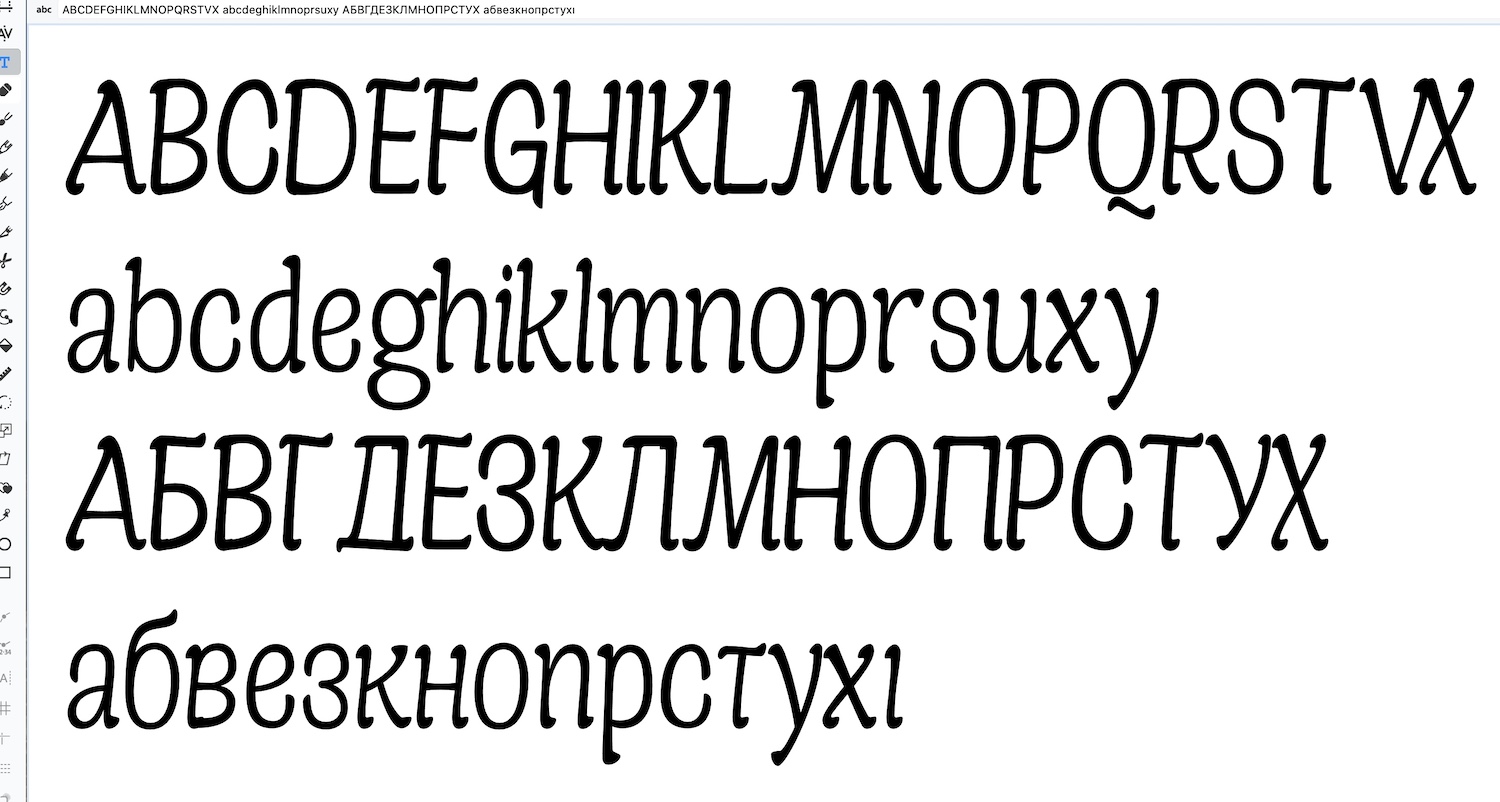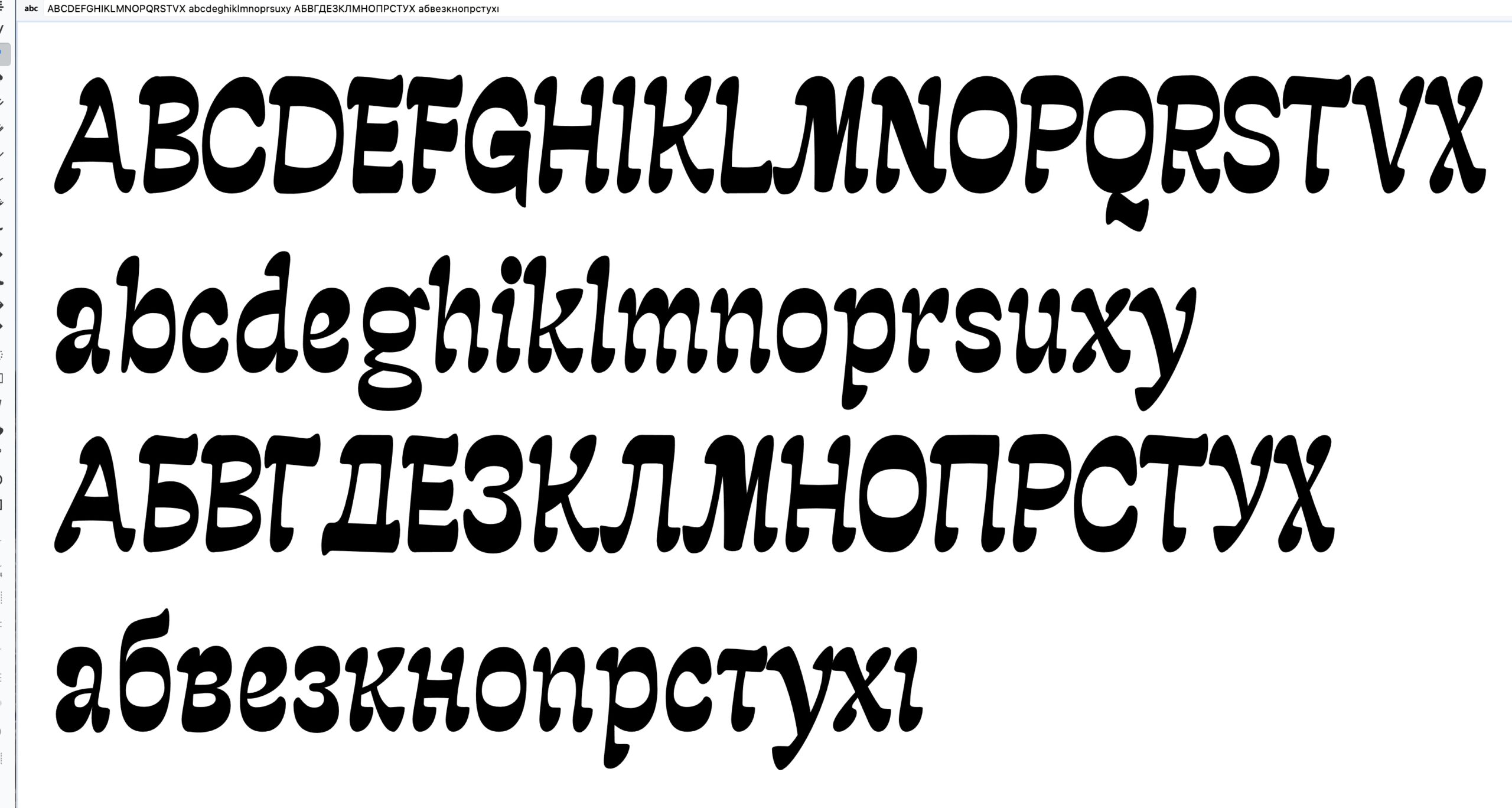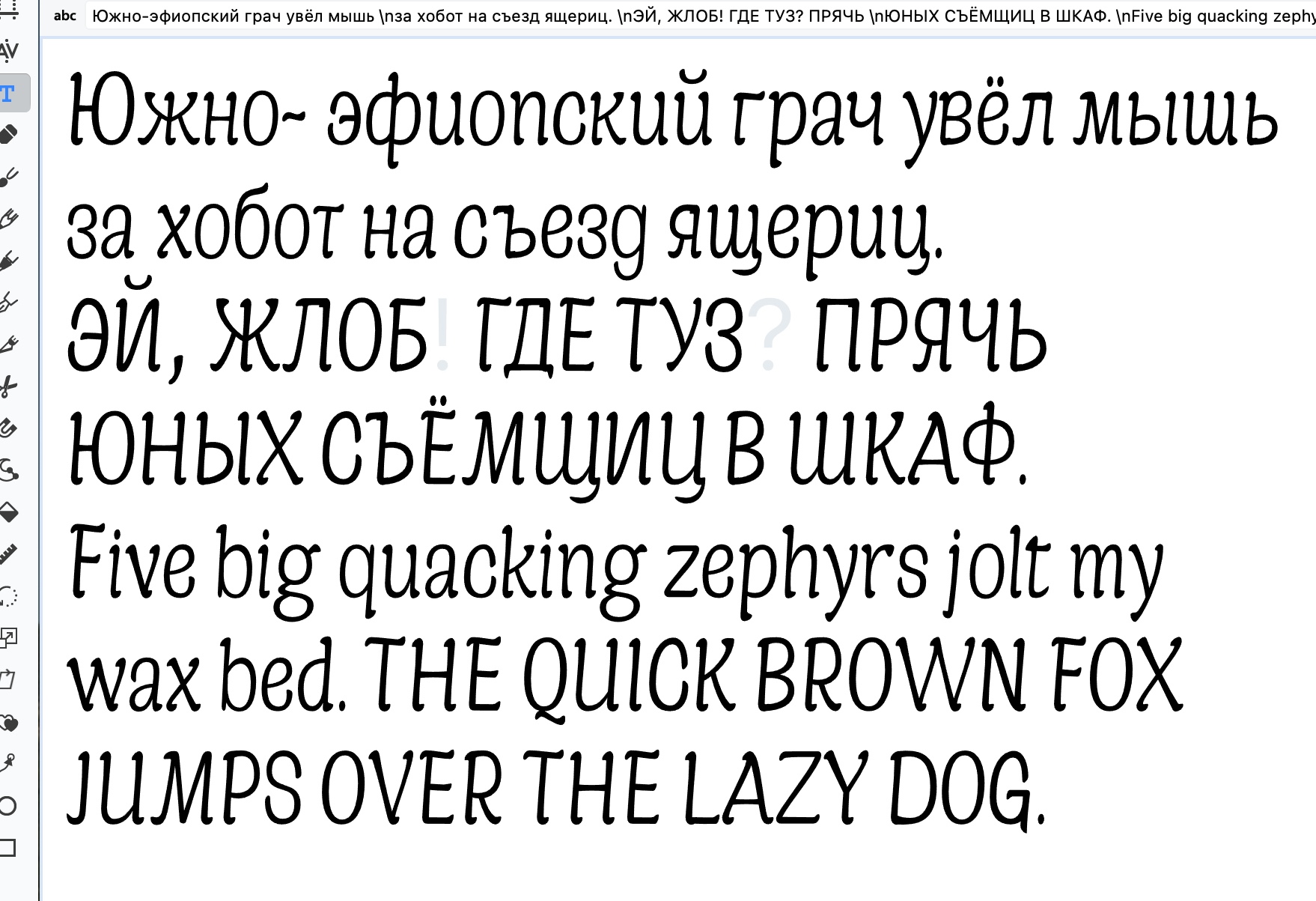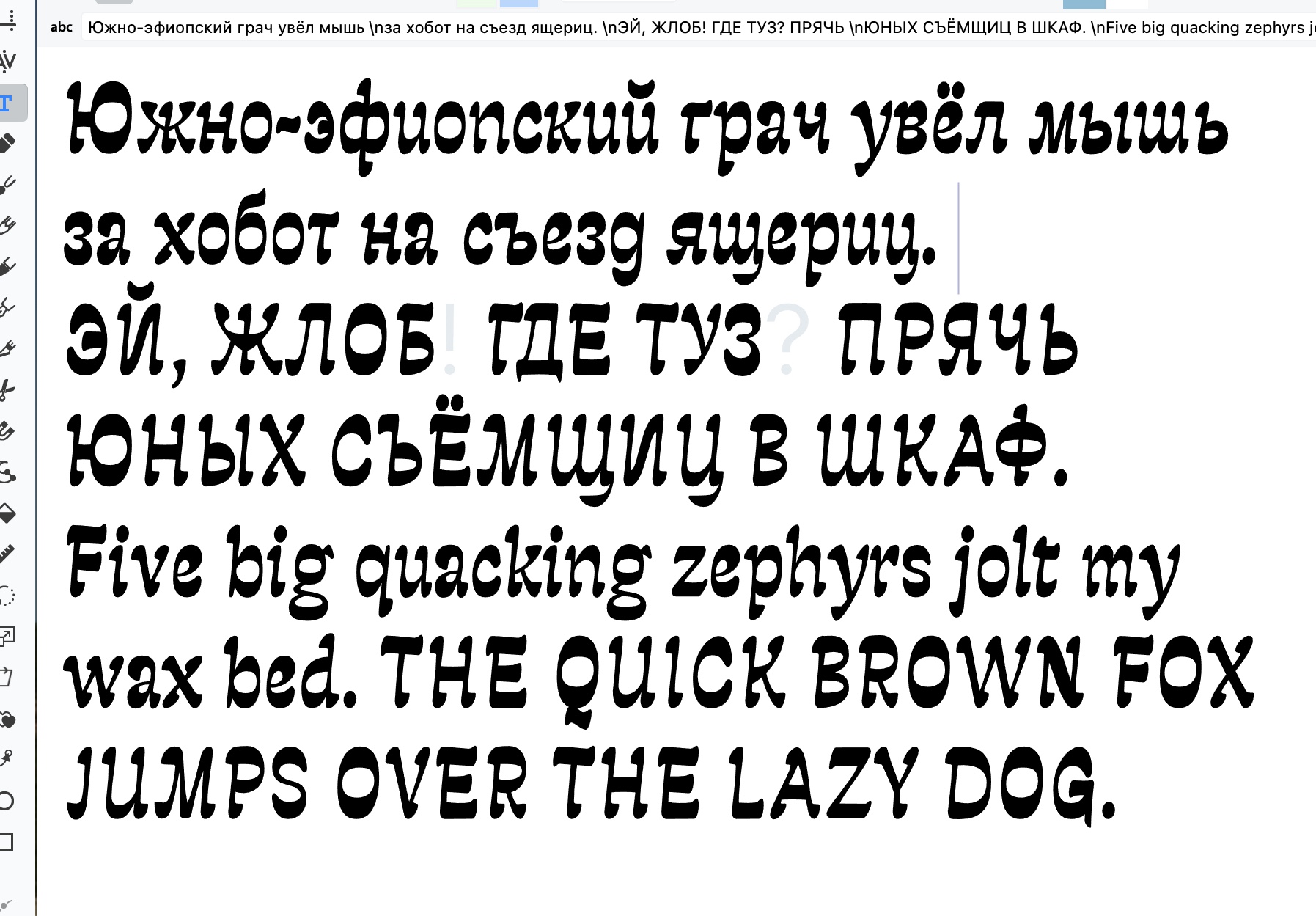
Куда ты, тропинка, меня завела…
Я так порадовался выходу Русалки на ПараТайпе, что в голову стали лезть мысли сделать еще шрифты с обратным контрастом. Вот, экспериментирую.
28.05.2026 – Продолжаю эксперименты.
30.05.26 – Основную кассу сделал. Но зачем???
30.05.26 – Блин, вы будете смеяться, но мне разонравилось реализовывать эту идею. Захотелось чего-то более антикво-подобного. Похоже на шрифт для Аллодов.